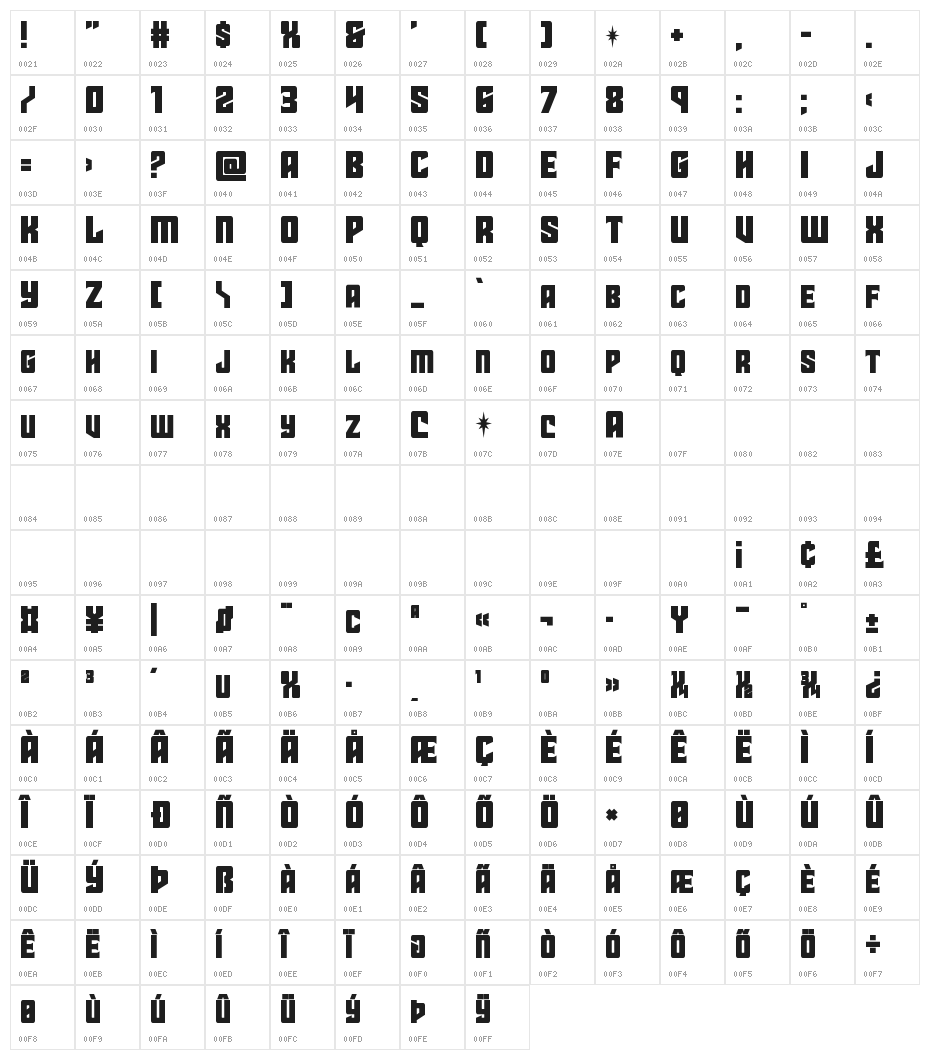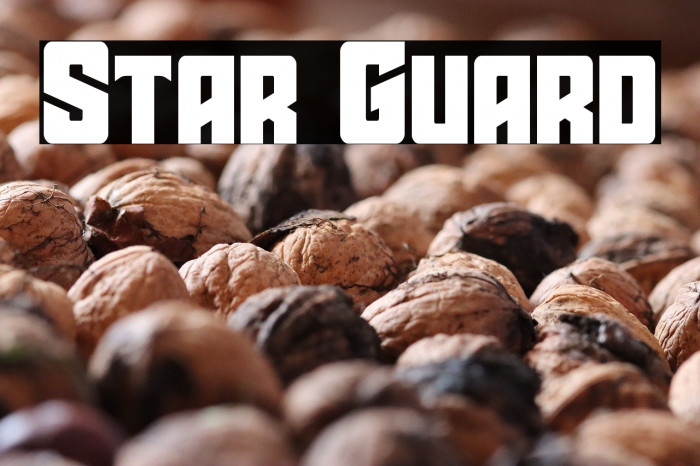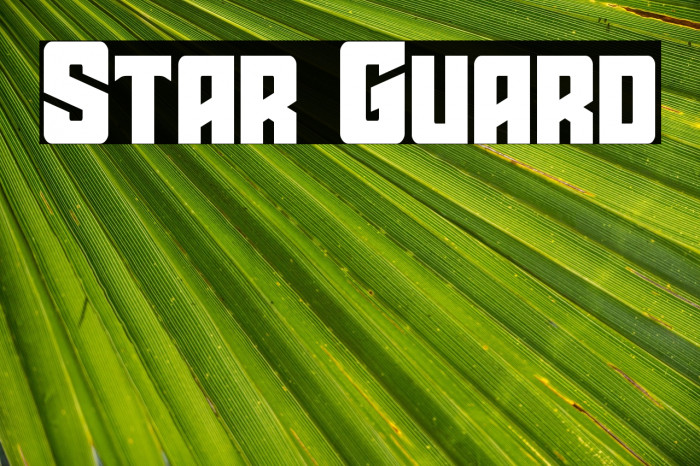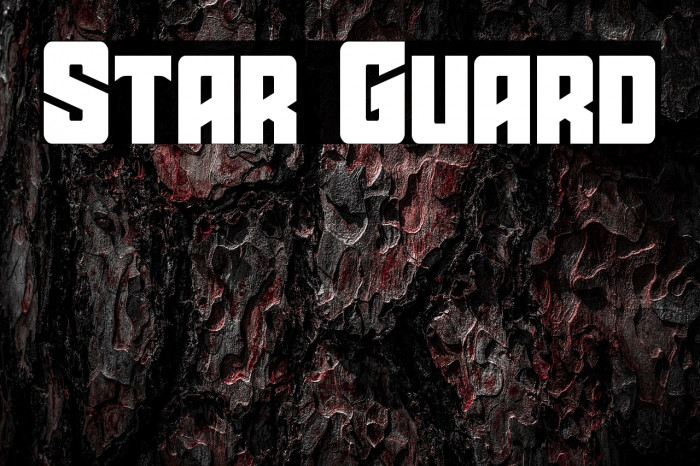
Star Guard Font
| Stile generale | Futuristic |
| Progetti proposti | Ideal for movie posters, video game titles, branding for tech companies, and any project needing a modern, bold look. |